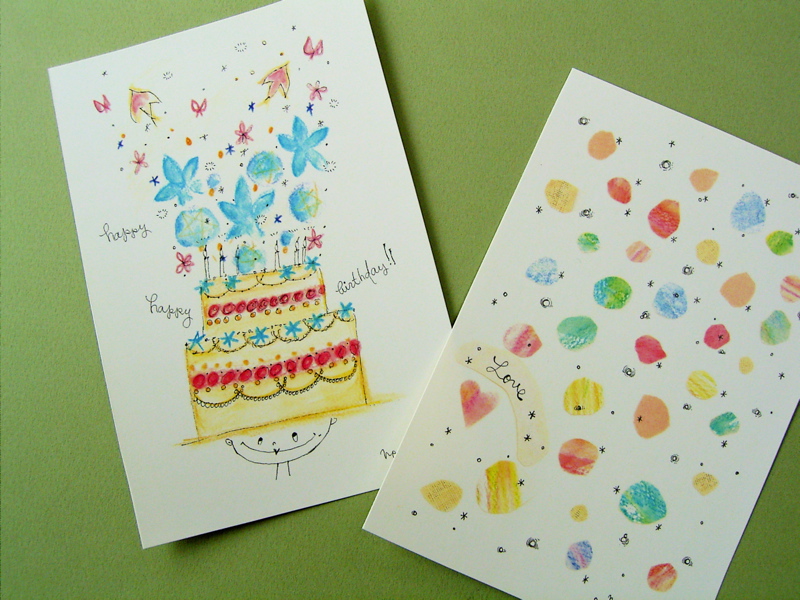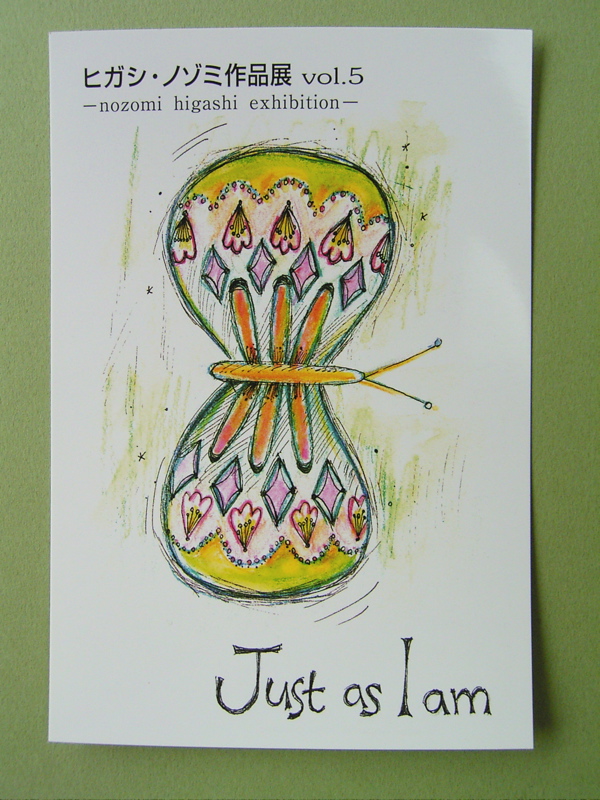
ひがしのぞみさんの個展
先週ヒガシ・ノゾミさんの個展を見に行きました。
場所はもうすぐ移転してしまう銀座の月光荘。この週は時間がなかったので、もう行けないかもと思いましたが、なんとかギリギリ30分だけでも!と暑い暑い日の午後、訪れました。
月光荘のお店の奥に小さなギャラリーがありますが、そこに水彩色鉛筆とペンの組み合わせの小さな作品が飾ってありました。
柔らかいけど鮮やか! というのが第一印象。可愛いイラストに今回はカリグラフィーも組み合わせた作品もありました。
ヒガシさんは福岡在住の方で、初島さつきさんの主宰するスタヂオ・ポンテでカリグラフィーを習い、また、水彩色鉛筆のクラスを教えてもいらっしゃるそうです。
イラストには所々にご本人のような女の子が登場したり、ニャンコがいたり、とても楽しいデザインです。黒の細い線との組み合わせが、柔らかいだけにならずに存在感を生んでいます。水彩色鉛筆ってこんなに風に表現豊かだったんですねー。